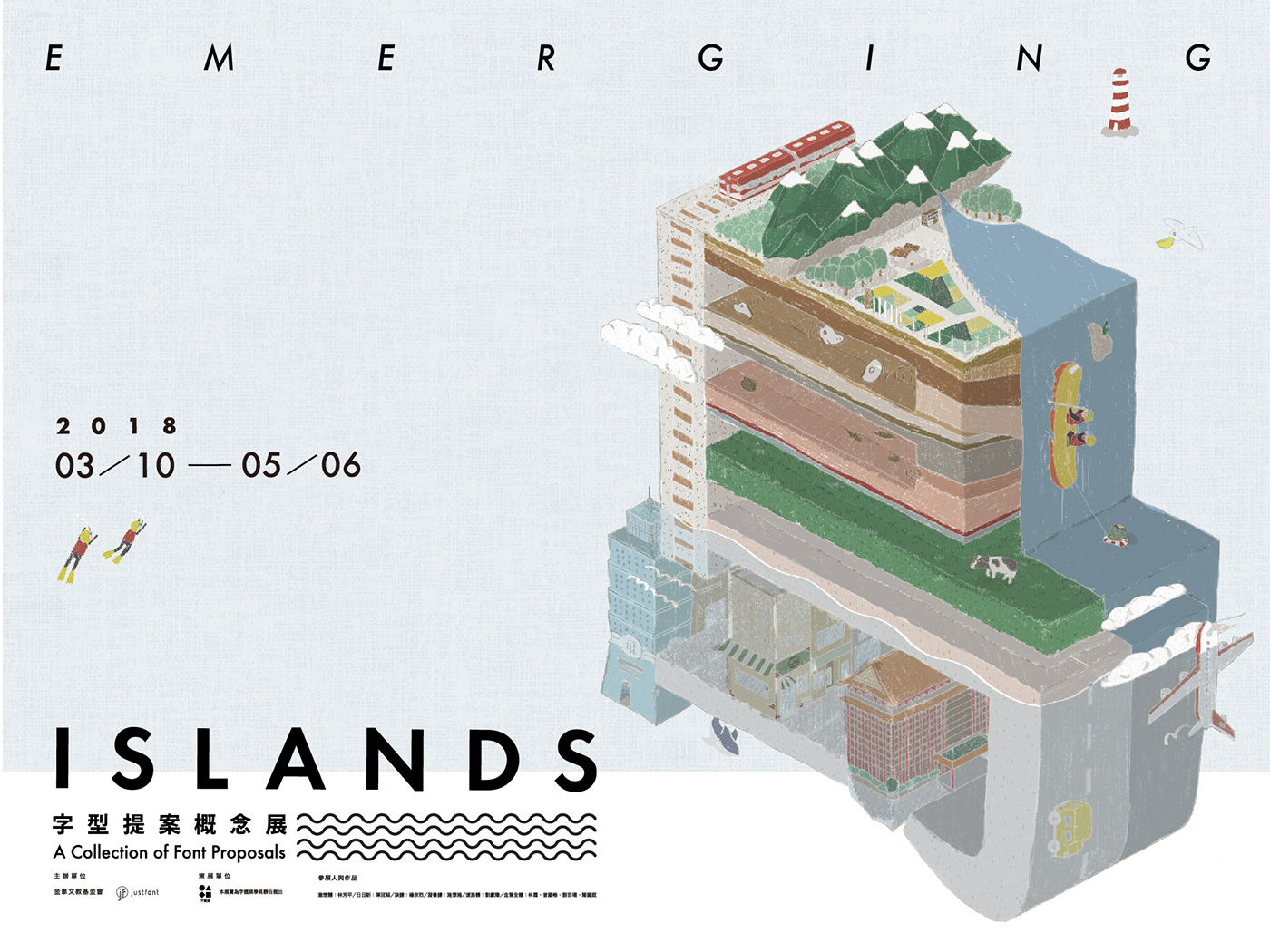
島:字型提案概念展-展覽視覺設計
|策展概念|
字型不僅是美麗的視覺組成,也是「現代設計的基礎建設」— 無數傑出思想必得仰賴字型使之具體。
漢字,數以萬計,設計大不易。字型設計師只能一字字地做,無法以機器取代之。
字的汪洋中,創作者一撇一捺,獨自堆起一小塊新生地。「島」是這些人的象徵。
但做字的人星羅棋布,多是孤島。默默完成作品,默默鼓勵自己。
他們的專業態度、不足為外人道的堅持,以及日夜努力的成果,往往不受社會矚目、稱頌。
雖然,這對他們成事的心願毫無差異,但長久以來,卻為社會帶來負面影響。
不了解字型設計的價值與貢獻,難有更多活水投入,就難以帶來正向循環。
因此我們提議,現在就把這些島嶼標示出來吧!讓全世界都看見他們的努力與堅持。
字的新土壤會慢慢鋪好。給點關注,投注些耐心,並把他們串連起來,陪伴、琢磨,期待這些島嶼,總有一天成為孕育新機的天堂。
|視覺設計概念|
島,為創作者的象徵,造字的創作過程,獨自築起心中理想的地貌。
島,也是台灣這塊土地和文化所積累的養分,提供創作者孕育出作品的豐富養分。
以字體構成環境空間
視覺設計以「島」字為核心,從二維平面轉向成三維的空間概念,將字體立體化、具象化的方式。傳達字體構成環境空間,環境空間也是字體本身。設計延伸應用以不同的構成形式在這立體的框架中,展示多樣性和可塑性,其中透過插畫的延展出各種不同的質地的圖騰,猶如島嶼地質的剖面,傳達台灣島嶼上文化的多樣性。
視覺行銷策略
島:字型提案概念展,以插畫為主要構成的視覺元素,希望拉近一般大眾對於字型設計的距離。
引發大眾對於字型設計的好奇和想像。
Visual design concept
Islands symbolize font designers, who create ideal landscapes in mind when designing their works. The idea of an island also represent the island of Taiwan itself, whose rich culture is an abundant offering for designers.
Exhibition Introduction
The Exhibition“Islands” features 6 Chinese font proposals by 6 Taiwanese designers and design team. Inspired by everyday things such as highway letterings to cream and tea, the creators attempt to make their proposals“emerge” to public agenda. By Illuminating stories behind each proposal and demonstrating how they would look when applied to everyday products, the exhibition focuses on conveying that type design is professional domain knowledge, which worths people's attention and appreciation.
Structuring a space trough type
We fostered our key visual design around the idea of an island. The Hanzi Character 島 (dǎo) was set with the typeface “Jinxuan”. However, it is not represented in a flat world view. It was transformed into a three-dimensional object, a creative space which had been structured through a typeface. We use such thinking as a tool to elaborate the concept of an island, with an attempt to explore a myriad of its meaning. The illustrations, in particular, exhibits a variety of textures and symbols, which are all possible sections of an island’s geography. We aim to convey the richness of its soil and the diversity of culture on such an island.
Illustration concept
Islands: a Collections of Font Design Concepts is an exhibition whose key visual was formed around illustration, instead of abstract typography composition. We appeal to the general public and aim to stimulate their curiosity and imagination of font design.
Islands symbolize font designers, who create ideal landscapes in mind when designing their works. The idea of an island also represent the island of Taiwan itself, whose rich culture is an abundant offering for designers.
Visual design concept
展場環境
|參展設計師與作品|
林芳平:激燃體
陳冠穎:日日新
施博瀚:凝書體
楊宗烈:淚體
劉獻隆:台灣道路體
Designers at justfont :金萱全糖
林芳平:激燃體
陳冠穎:日日新
施博瀚:凝書體
楊宗烈:淚體
劉獻隆:台灣道路體
Designers at justfont :金萱全糖